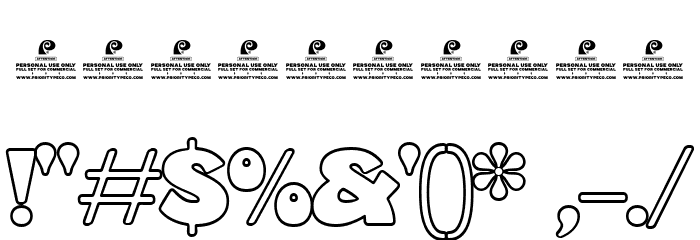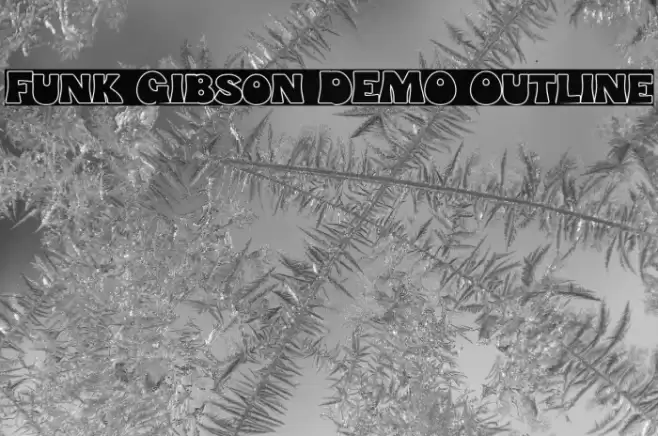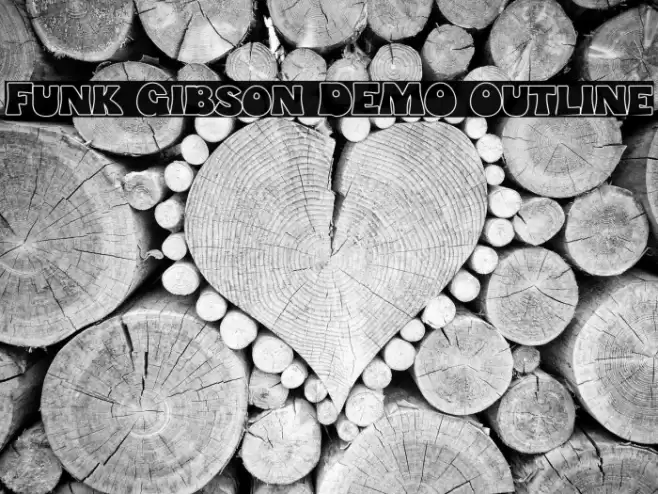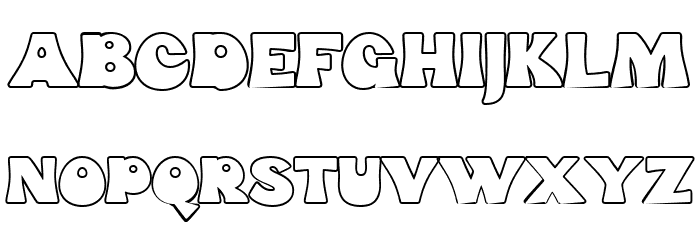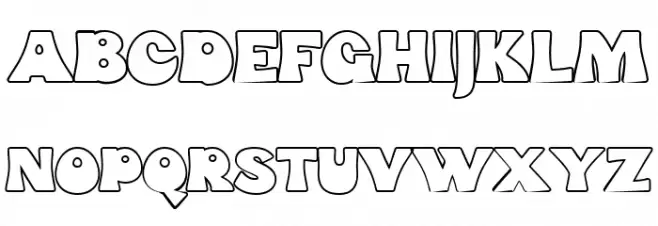
Funk Gibson DEMO Outline Font
| समग्र शैली | Playful, Cartoonish |
| उपयोग का मामला | Headlines, Logos, Posters |
| सुझाए गए प्रोजेक्ट | Ideal for children's books, comic strips, playful branding, and party invitations. |